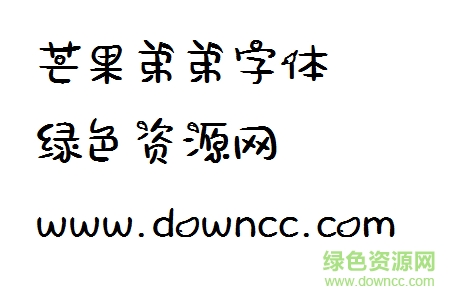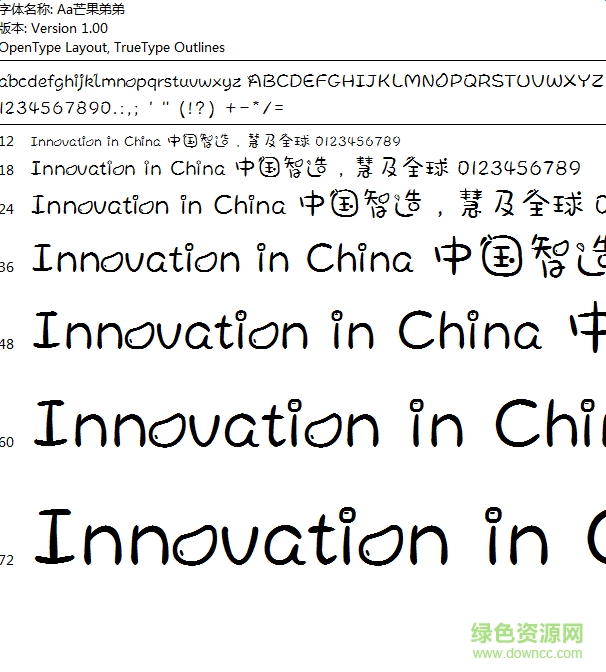
芒果弟弟字體是一款小清新風(fēng)格芒果字體,字體以芒果的外形為基礎(chǔ),盡顯其清新可愛(ài)的字體韻味,整體效果十分自然脫俗,喜歡就來(lái)綠色資源網(wǎng)下載使用吧!
芒果弟弟字體是一款可愛(ài)中文字體,該字體筆畫(huà)細(xì)膩,大字效果突出且引人注目;并且最大程度還原作者書(shū)寫(xiě)字形,細(xì)節(jié)表現(xiàn)完整,且字庫(kù)完整,可以廣泛應(yīng)用于名片設(shè)計(jì)、新聞媒體、宣傳海報(bào)、ppt、影視制作以及內(nèi)容用字等領(lǐng)域。
該字體屬于非常迷人的中文藝術(shù)字體,字體筆畫(huà)隨意,非常的文雅脫俗,整體效果十分時(shí)尚好看,感興趣的朋友歡迎免費(fèi)下載使用!